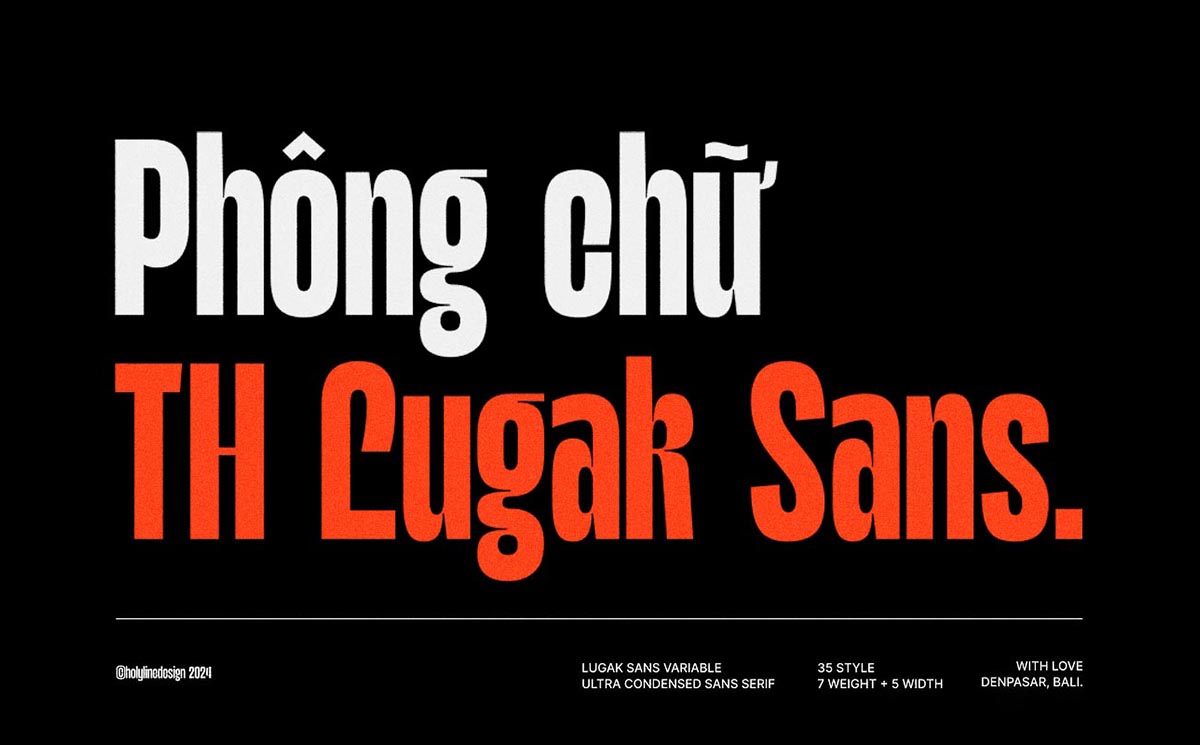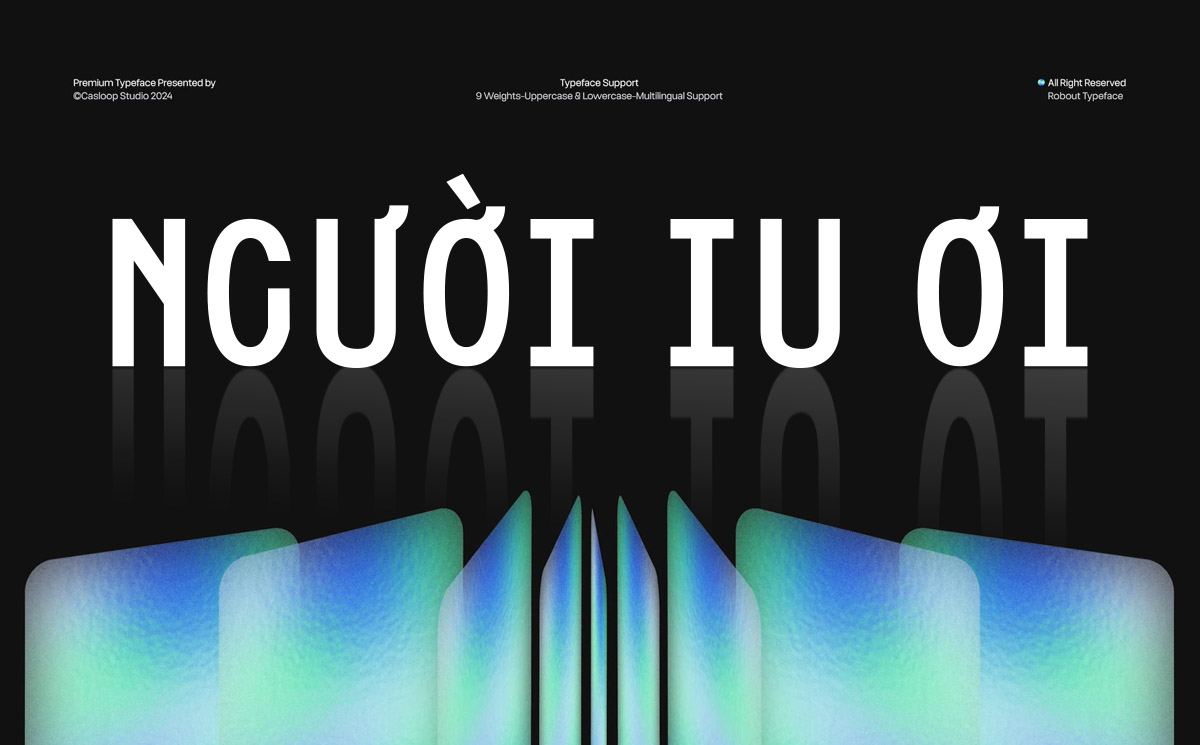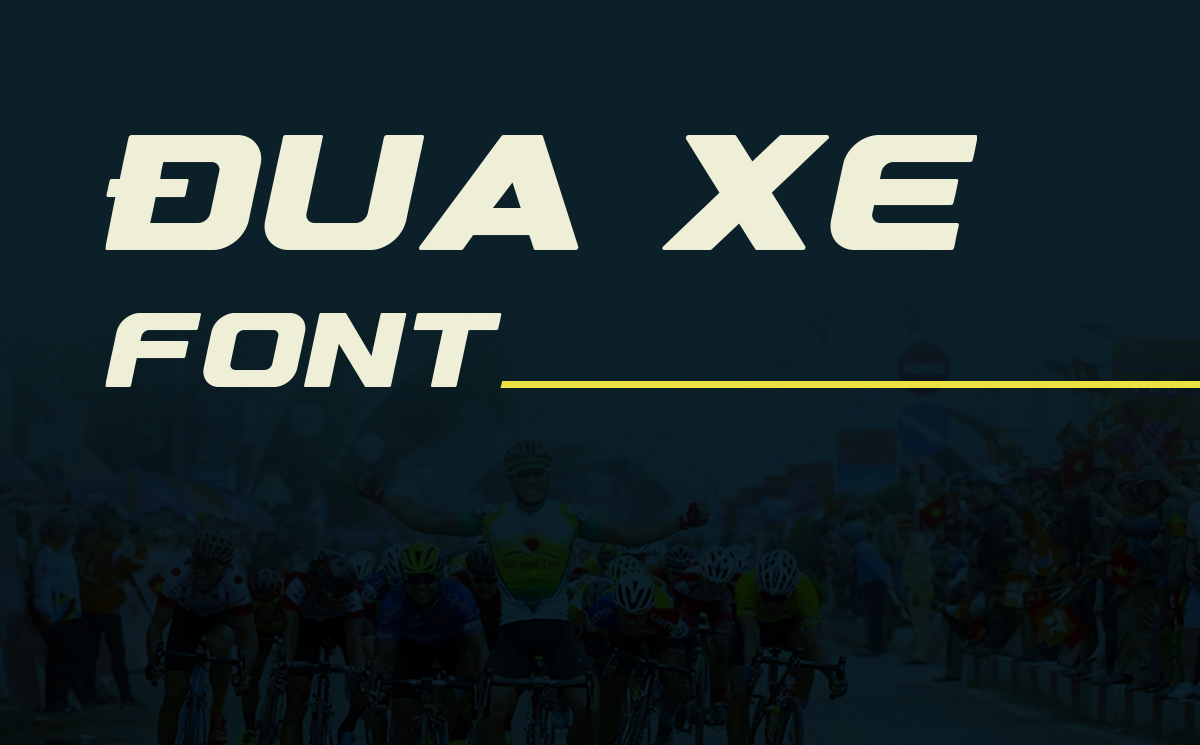
Khám phá 17 font chữ công nghệ Việt hóa đẹp nhất 2025 – hiện đại, dễ đọc, hỗ trợ tiếng Việt đầy đủ, phù hợp thiết kế UI/UX, app, poster và branding.
Nếu bạn đang tìm một font chữ công nghệ vừa hiện đại, dễ đọc lại hỗ trợ tiếng Việt đầy đủ thì bài viết này là dành cho bạn.
Chúng tôi đã tuyển chọn 17 font chữ công nghệ Việt hóa đẹp, phù hợp cho thiết kế UI/UX, banner phần mềm, app mobile hay các dự án công nghệ. Mỗi font đều mang phong cách rõ ràng, file nhẹ, dễ dùng trên cả Photoshop, Canva và Figma.
Dù bạn là designer chuyên nghiệp hay chỉ mới bắt đầu, danh sách này sẽ giúp bạn chọn được font chữ công nghệ đẹp và phù hợp nhất cho năm 2025.
Phông Chữ Công Nghệ Là Gì?
Font chữ công nghệ là nhóm font mang dấu ấn hiện đại, tương lai và kỹ thuật số. Kiểu chữ này thường sử dụng trong các thiết kế liên quan đến AI, blockchain, app mobile, giao diện người dùng (UI/UX), hoặc các sự kiện kỹ thuật số.
Với đường nét rõ ràng, dứt khoát, có thể bo góc nhẹ hoặc hiệu ứng LED/Pixel, những font này không chỉ gây ấn tượng mạnh về thị giác mà còn giúp nhận diện thương hiệu trở nên chính xác và chuyên nghiệp hơn.
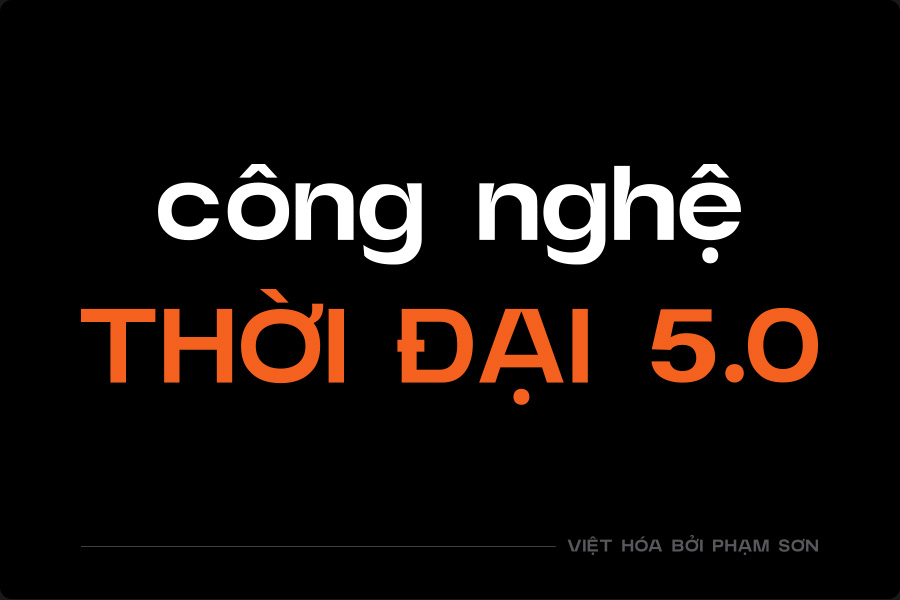
Tiêu Chí Chọn Font Chữ Công Nghệ Chuẩn Thiết Kế 2025
Để font phát huy hết hiệu quả, bạn nên chọn dựa trên các tiêu chí sau:
- Tương thích tiếng Việt: hỗ trợ đầy đủ dấu, tránh lỗi hiển thị.
- Phong cách rõ ràng: phù hợp logo, poster, giao diện app, giao diện hệ thống.
- Hiệu suất cao: file nhỏ, không gây trễ trang web hoặc app.
- Ứng dụng linh hoạt: hoạt động tốt trên Canva, Figma, Photoshop...
Top 17 Font Chữ Công Nghệ Việt Hóa Đẹp Nhất 2025
TH Lugak Sans – Font chữ công nghệ mạnh mẽ
Lugak Sans mang đến cảm giác chắc chắn nhờ các đường nét đều đặn, hình học rõ ràng, nhưng không quá cứng nhờ phần bo tinh tế ở góc chữ. Thiết kế tạo độ mở hợp lý giữa các ký tự, giúp văn bản nổi bật mà không rối mắt. Với cấu trúc mạnh mẽ nhưng vẫn linh hoạt, font này cực kỳ phù hợp khi bạn cần truyền tải tinh thần công nghệ hiện đại một cách chỉn chu, thẩm mỹ.
Metropolis (18 kiểu) – Font chữ sans-serif đa trọng lượng
Metropolis gồm đến 18 biến thể trọng lượng – từ nhạt đến đậm – giúp bạn dễ dàng kết hợp cho tiêu đề lẫn nội dung thường. Nét chữ hình học, gọn ghẽ với các góc vuông được xử lý gọn gàng, tạo cảm giác cao cấp, hiện đại. Phù hợp cho các dự án thiết kế sản phẩm công nghệ muốn giữ sự nhất quán mà vẫn linh hoạt biểu cảm.
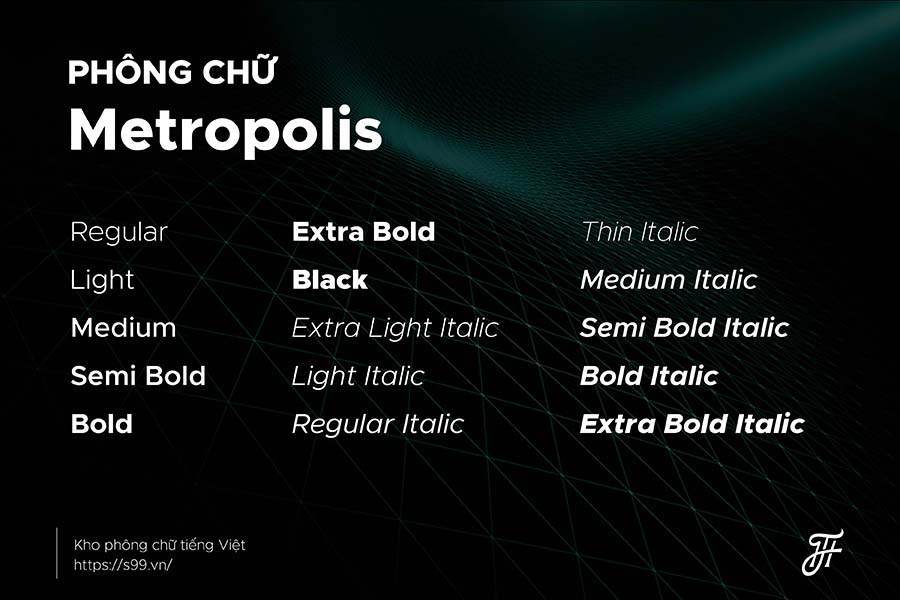
TH Cutta – Font Mảnh Mai Gọn Gàng
Nét chữ mảnh, nhẹ của Cutta gợi sự thanh thoát, nhưng ẩn chứa độ chính xác cao nhờ các đoạn gãy được xử lý khéo. Một vài ký tự có chi tiết cắt khuyết nhẹ như chữ “g”, “a” tạo điểm nhấn độc đáo – rất phù hợp cho giao diện thương hiệu hoặc thiết kế web muốn thể hiện sự tối giản nhưng có chiều sâu.
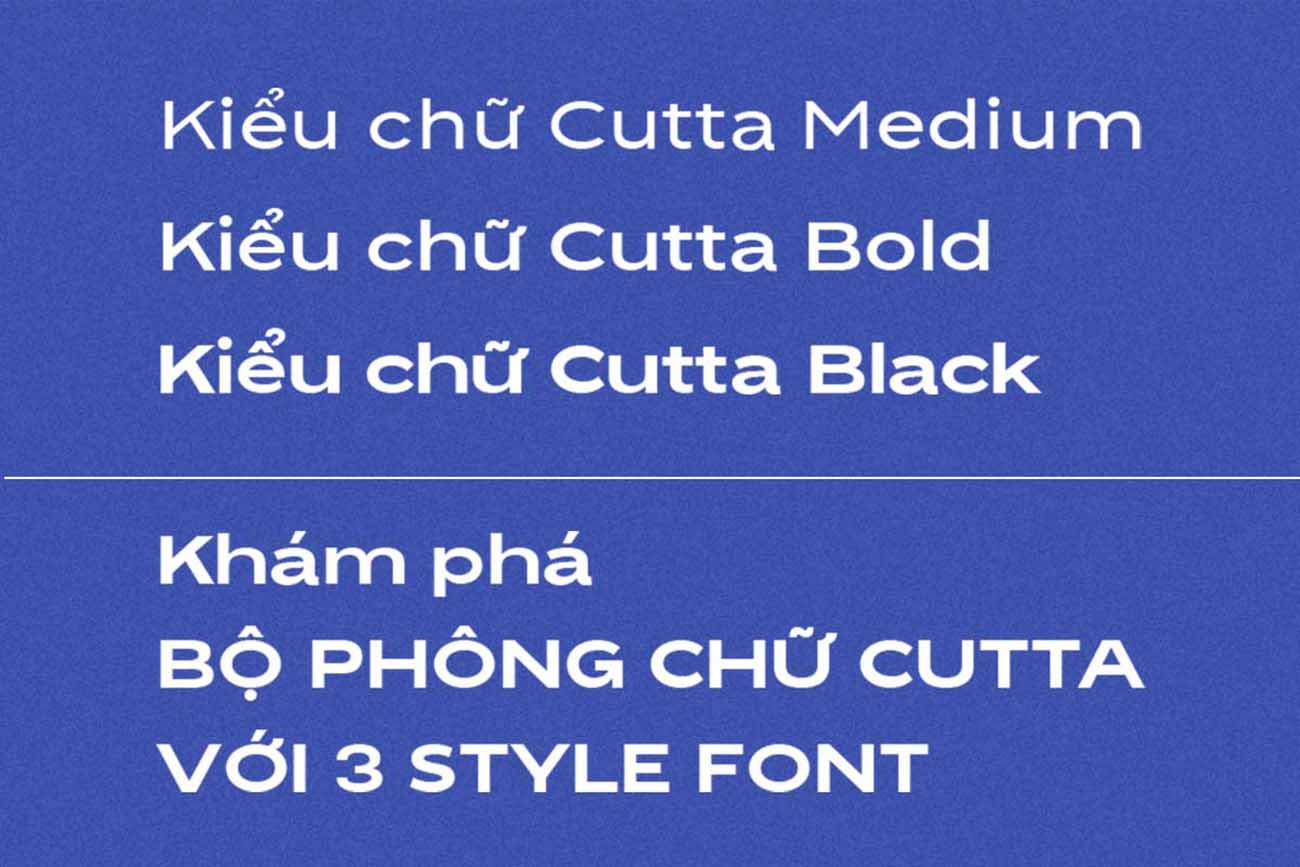
Manisans – Font Thanh Lịch Dễ Đọc
Manisans mang đến cảm giác cởi mở nhờ nét cong mềm và độ nghiêng rất nhẹ ở một số ký tự. Chữ cái tròn đều, không gian mở rộng vừa đủ khiến từng đoạn văn luôn giữ được nhịp thở dễ chịu khi nhìn lâu. Font lý tưởng cho các dự án digital muốn giữ tính thẩm mỹ cao mà không gây mỏi mắt khi đọc.
Việt hóa bởi: Phạm Sơn - Admin S99, Fontdep.vn
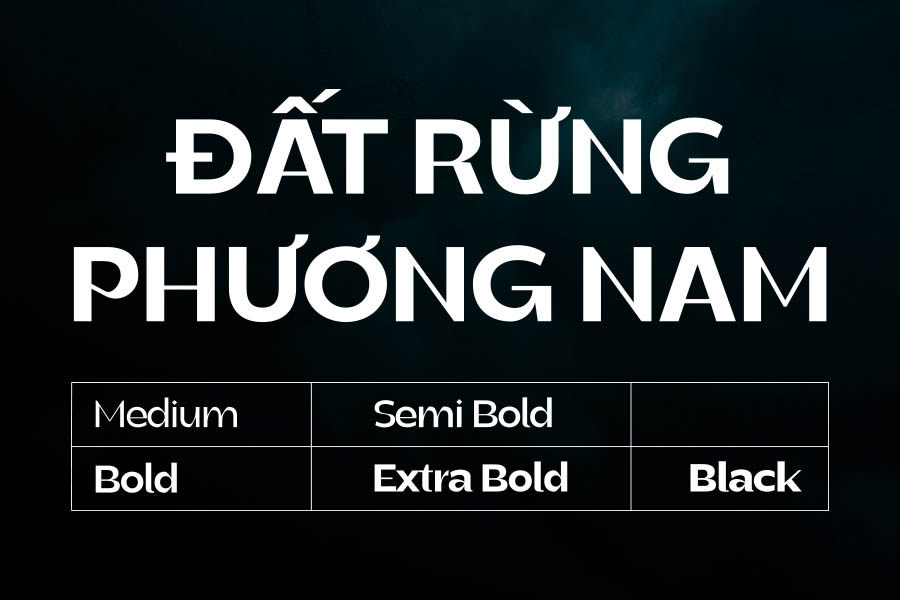
TH Artega – Font Tối Giản Rõ Nét
Artega sở hữu kết cấu chữ ổn định với các đường thẳng mạnh mẽ và nét cong tròn được xử lý chính xác. Chân chữ hơi vuốt nhẹ khiến tổng thể không bị cứng nhắc, đồng thời tăng tính thân thiện khi dùng ở kích thước nhỏ. Font hợp với các thiết kế thiên về hệ thống hoặc dashboard cần sự trực quan, khoa học.
Tác giả gốc: Yukita Creative
Việt hóa bởi: Phạm Sơn - Admin S99, Fontdep.vn
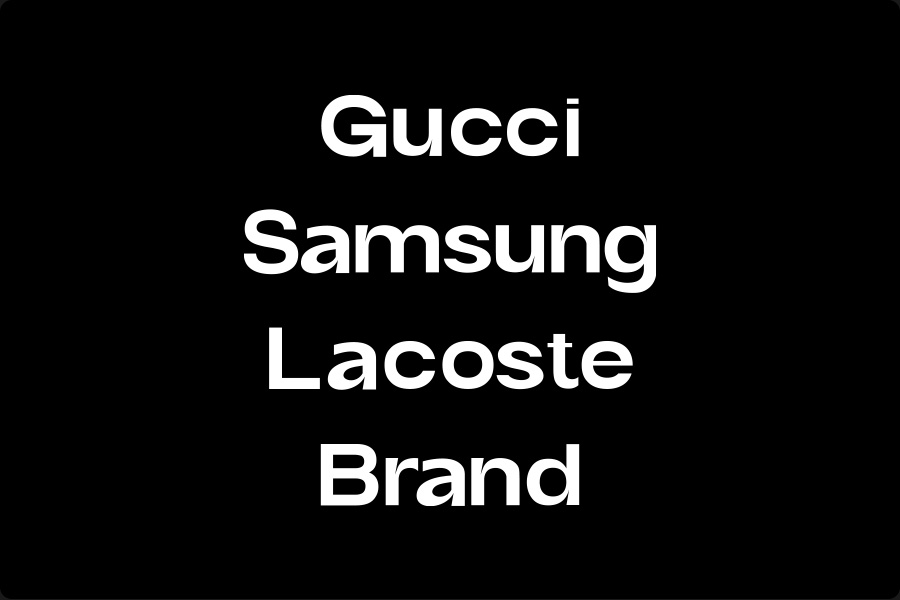
TH Neo Cybern – Font Sci-fi Tương Lai
Với các nét cắt ngang độc đáo ở chữ E và R, Neo Cybern tạo ra không khí của một thế giới công nghệ viễn tưởng. Chữ cái dày dặn, đều đặn và hình khối chắc chắn, mang đậm tinh thần cyberpunk. Khi được đặt vào bối cảnh như tiêu đề game hoặc poster AI, font này dễ dàng trở thành điểm thu hút đầu tiên.
Tác giả gốc: Storytype Studio (Letterena Studios)
Việt hóa bởi: Phạm Sơn - Admin S99, Fontdep.vn
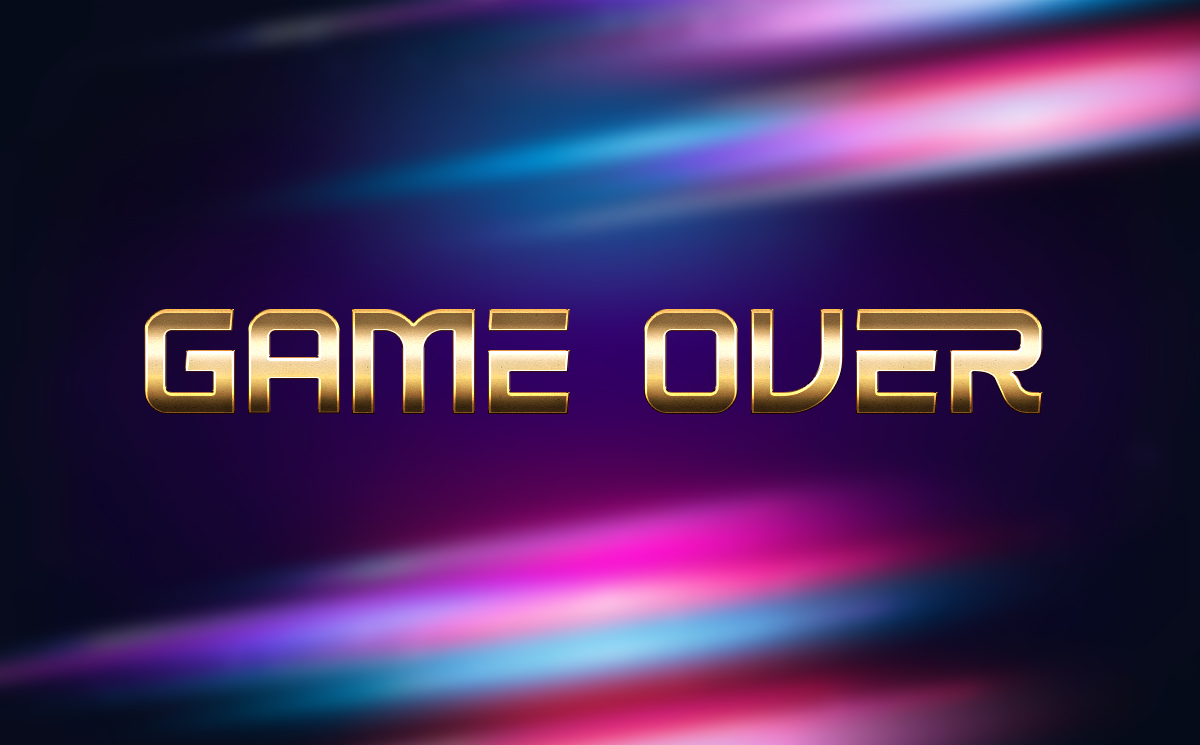
TH Grotley – Font Công Nghệ Cao Cấp
Grotley là kiểu chữ mang đậm hơi hướng sang trọng nhờ sự đồng đều trong chiều cao và độ tròn của các ký tự. Nét chữ hơi dày, được xử lý bo nhẹ ở một số điểm giúp font vừa đủ nghiêm túc nhưng không quá nặng nề. Một lựa chọn lý tưởng cho thương hiệu muốn kết hợp giữa yếu tố công nghệ và hình ảnh cao cấp.
Kết Luận
Chọn đúng font chữ công nghệ không chỉ giúp tăng độ độc đáo mà còn góp phần xây dựng hình ảnh chuyên nghiệp cho thiết kế. Dù là giao diện web, banner AI, hay poster về chủ đề blockchain, một font tốt sẽ biến nội dung của bạn trở nên rõ ràng và đắt giá hơn.